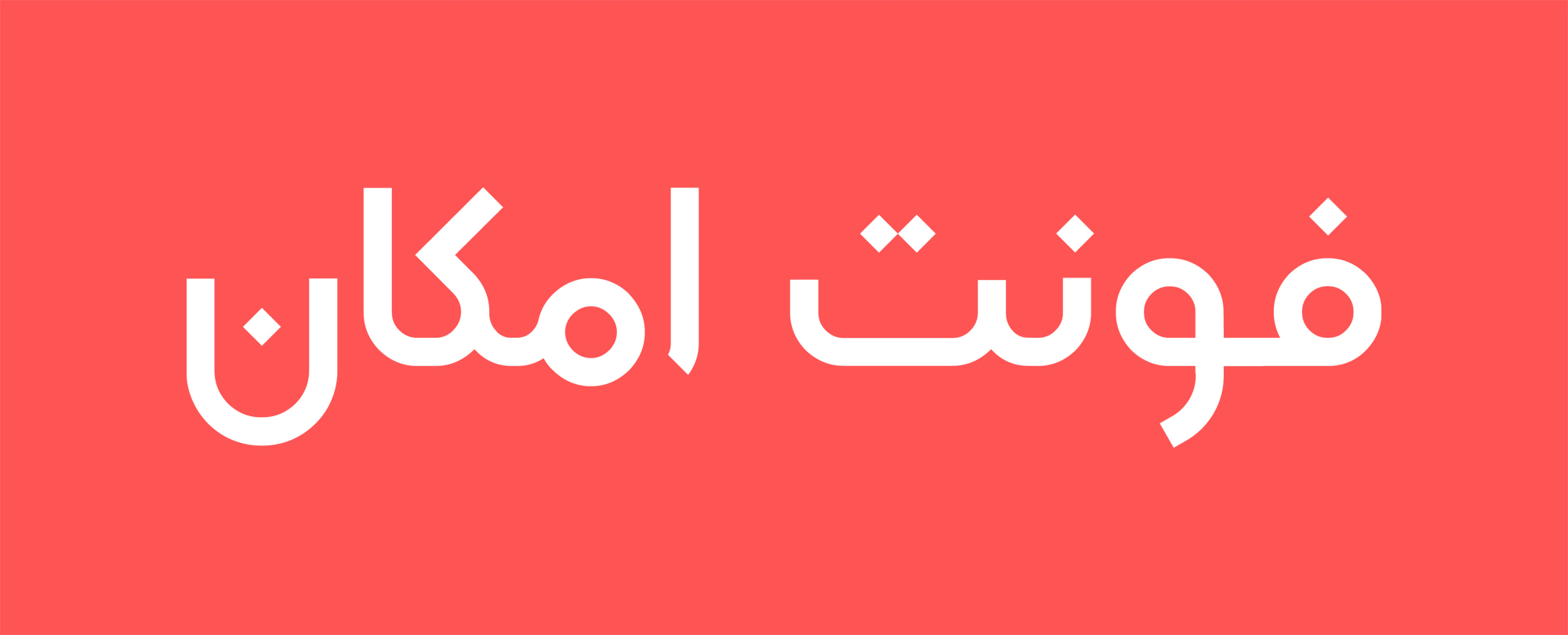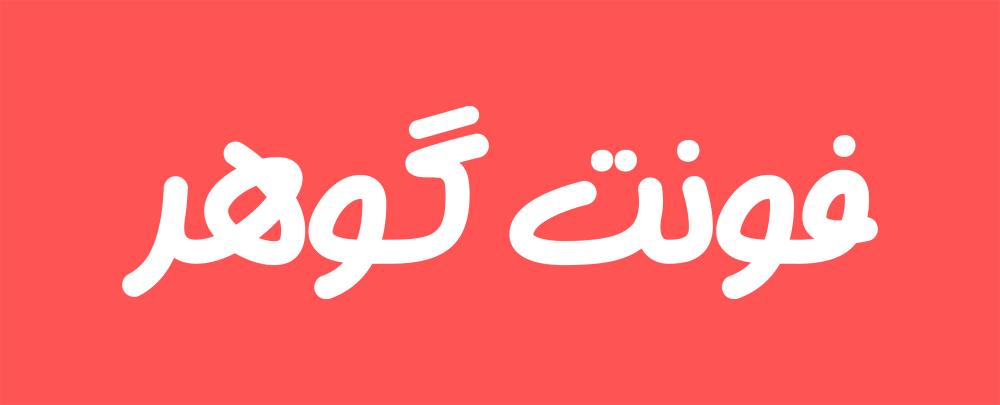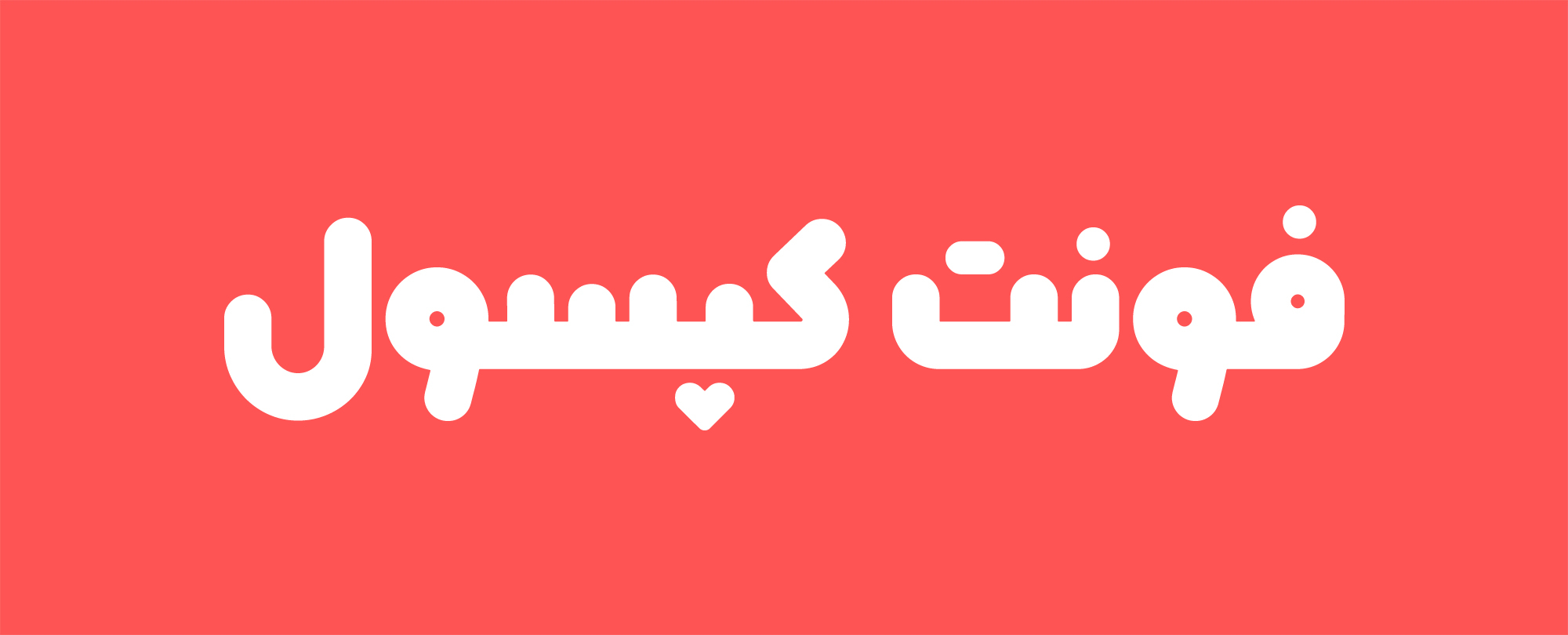
فونت امکان یک تایپفیس هندسی است که بر اساس اسکلتی خطی شکل گرفته است.
ابوالفضل رهروان طراح این فونت با پایبندیِ سختگیرانه بر ساختار هندسی، فونتی را طراحی کرده است که در عین سادگی جدید و نوآورانه است.
فونت امکان با افزایش ضخامت دارای ۴ وزن شده است. (باریک، معمولی، بولد و سیاه)، با دایره شده مقطعِِ خط، استایل گرد (Rounded) پدید آمده است و در نهایت یک فونت تزئینی بر اساس نازکترین وزن ساخته شده است و یک فونت درون خط (Inline) بر اساس حالت گرد تا در مجموع خانواده فونت امکان دارای ۹ عضو باشد.
فونت گوهر یک فونت دست نویس ضخامت یکسان (منولاین) است که توسط مصطفی اوجی طراحی شده است. مصطفی اوجی طراح فونت گوهر از اولین طراحان تایپ ایران است که این حرفه را به صورت آکادمیک آموخته است. مصطفی اوجی سالها، استاد درس طراحی حروف در دانشگاه هنر تهران بوده است و تا کنون فونتهای فارسی و عربی بسیاری را طراحی کرده است.
فونت گوهر ساختار فشرده و اصطلاحاً جمع و جور دارد برای همین سطرهای منسجم و فشردهای ایجاد میکند. حرکات حروف به رغم رهایی حرکات قلم، فرمهای کنترل شدهای دارند.
فونت گوهر در ۵ وزن: نحیف، لایت، متوسط، بولد و سیاه طراحی و ارائه شده است که با کمک آن میتوانید کنترل خوبی روی دسته بندی نوشتهها داشته باشید.
کپسول را می توان در دسته فونت های نمایشی و هندسی قرار داد. ضخامت یکسان، استایل گرد و منحنی بودن گوشهها به جذاب شدن و سادگی فونت کمک بسیار کرده است.
از ویژگی های ظاهری فونت کپسول میتوان به؛ مینیمال بودن، بامزه، نرم و لطیف، سنگین، تپل، مهربان، فانتزی و ... اشاره کرد.
کپسول بیشتر مناسب موضوعات تجاری و مدرن مثل صنایع بسته بندی (موادغذایی ومواد شوینده) است و برای عنوان فروشگاه، نشریات و کتاب های کودک، برندهای تجاری و... کاربرد دارد.
ابر خانواده حروف انجمن به صورت اختصاصی و با حمایت «انجمن صنفی طراحان گرافیک ایران» تولید شده است. انجمن به لحاظ زیبایی، دیزاین استاندارد و تنوع جامع وزنها توانست برنده جایزهی اول دوسالانه سرو نقرهای ۹۸ شود.
این فونت برای بهبود کیفیت، هر ساله به روزرسانی و همواره پشتیبانی میشود. با توجه به امکانات جدید و جامع در آخرین بهروزرسانی، زین پس نسخه جدید انجمن را با پسوند مَکس (Max) خواهید دید.
انجمن مَکس دارای ۱۳ وزن است که تمامی این وزنها در سبکهای ایتالیک (Italic) و فشرده (Condense) نیز طراحی شدهاند. انجمن یکی از جامعترین فونتهایی است که طراحان و کاربران میتوانند در سبد دیزاین خود داشته باشند. گستره وسیع وزنها دست طراحان را برای استفاده نمایشی و سایز کوچک از فونت باز میگذارد.
فونت پیدا ساختاری هندسی دارد اما بعضی از ویژگیهای خطوط سنتی همچون نسخ نیز در آن دیده میشود.
ناصر خادم پیش از این فونت کلمه را طراحی کرده است. فونت کلمه در مدت زمان کوتاهی پس از انتشار به قلمی پر طرفدار در گرافیک تجاری و تولید محتوای دیجیتال تبدیل شد و اکنون فونت پیدا نیز از همان ویژگیهای جذاب فونت کلمه یعنی ساختار هندسی، کنتراست ضخامت حداقل و شکل حروف نوآورانه بهره مند است. اما فونت پیدا به نسبتِ کلمه دارای خانواده کاملتر، خوانایی بیشتر و در نتیجه برای متن مناسبتر است.